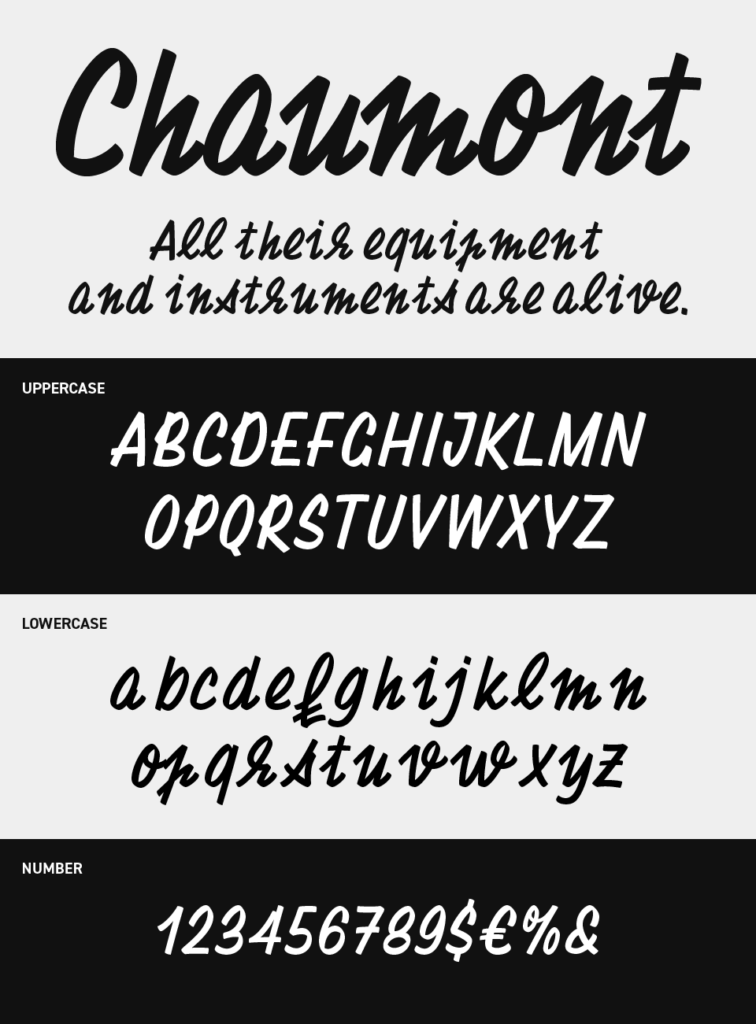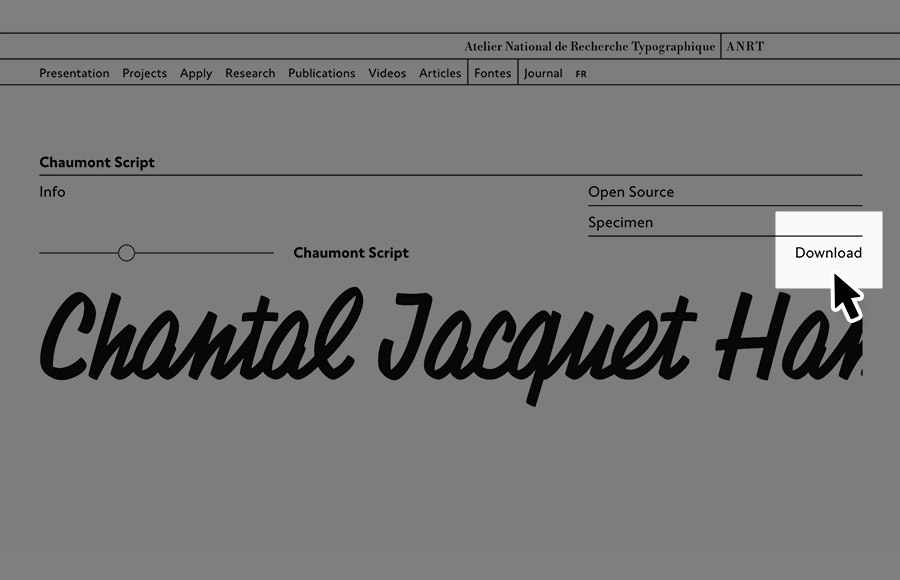
Chaumontフォントは、勢いのあるブラッシュストロークが魅力のエネルギッシュなスクリプト書体です。
太めなマーカーで書かれたような太くかすれた筆致が文字に躍動感を与え、タイトルに使うだけで一気にライブ感のある空気を生み出すフォントです。
ストリートカルチャーや音楽イベント、アパレルのビジュアルなど、感情を前面に出したいデザインにぴったりなフォントです。